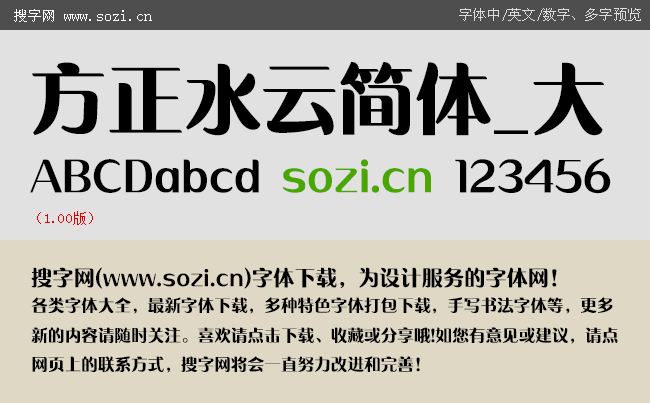
方正水云簡體_大
搜字網(wǎng)提供一款方正水云簡體_大中文字體下載,方正水云體筆形由至簡的直線與弧線構(gòu)成,拋棄細(xì)節(jié),追求用最簡潔元素營造豐富而統(tǒng)一的視覺氛圍。字體簡潔流暢、圓潤柔美,如行云流水般平緩易讀,“水云體”因此意象得名,適用于產(chǎn)品設(shè)計(jì)、包裝印刷、報(bào)刊雜志、正文標(biāo)題、繪畫創(chuàng)作等廣告設(shè)計(jì)場(chǎng)合使用。